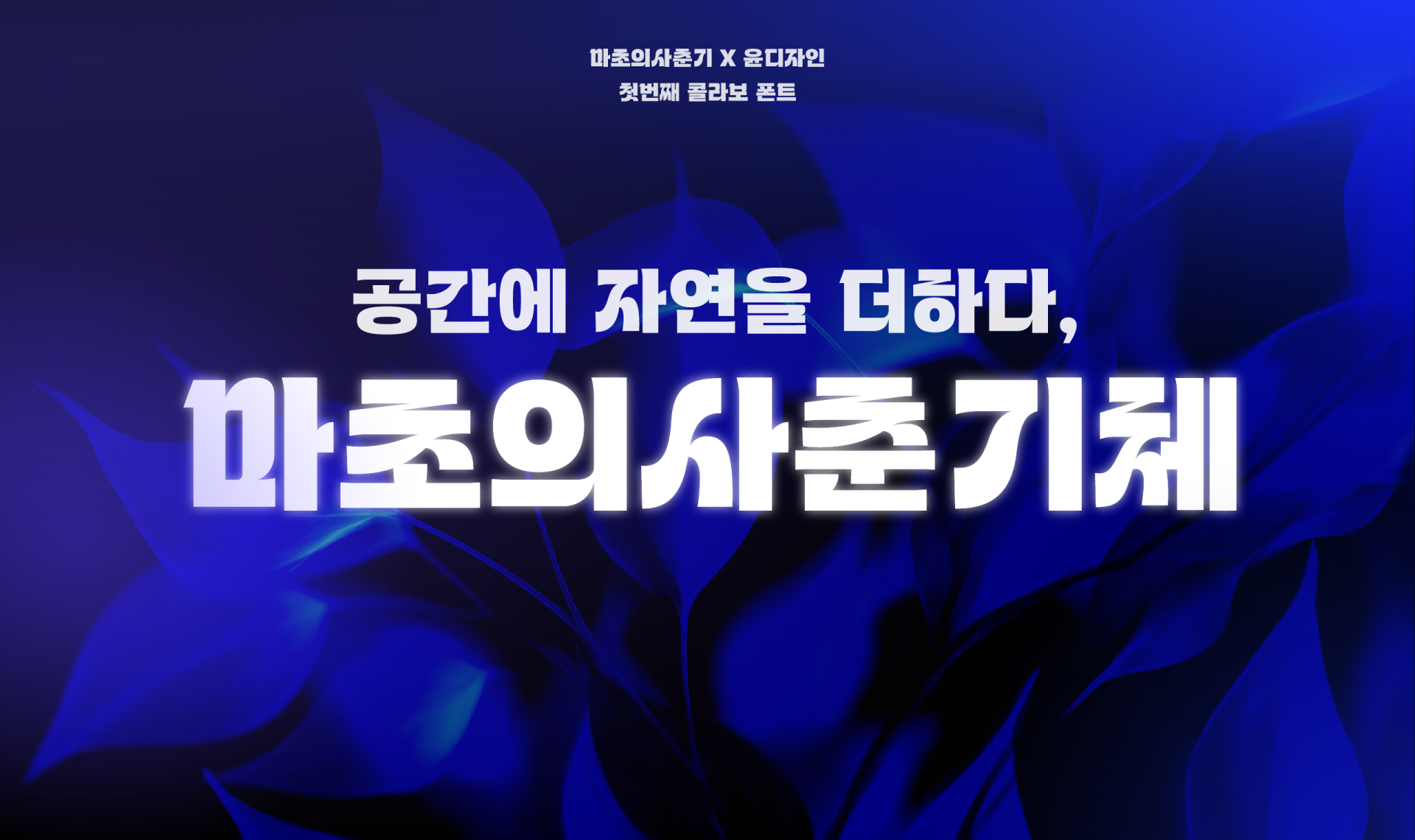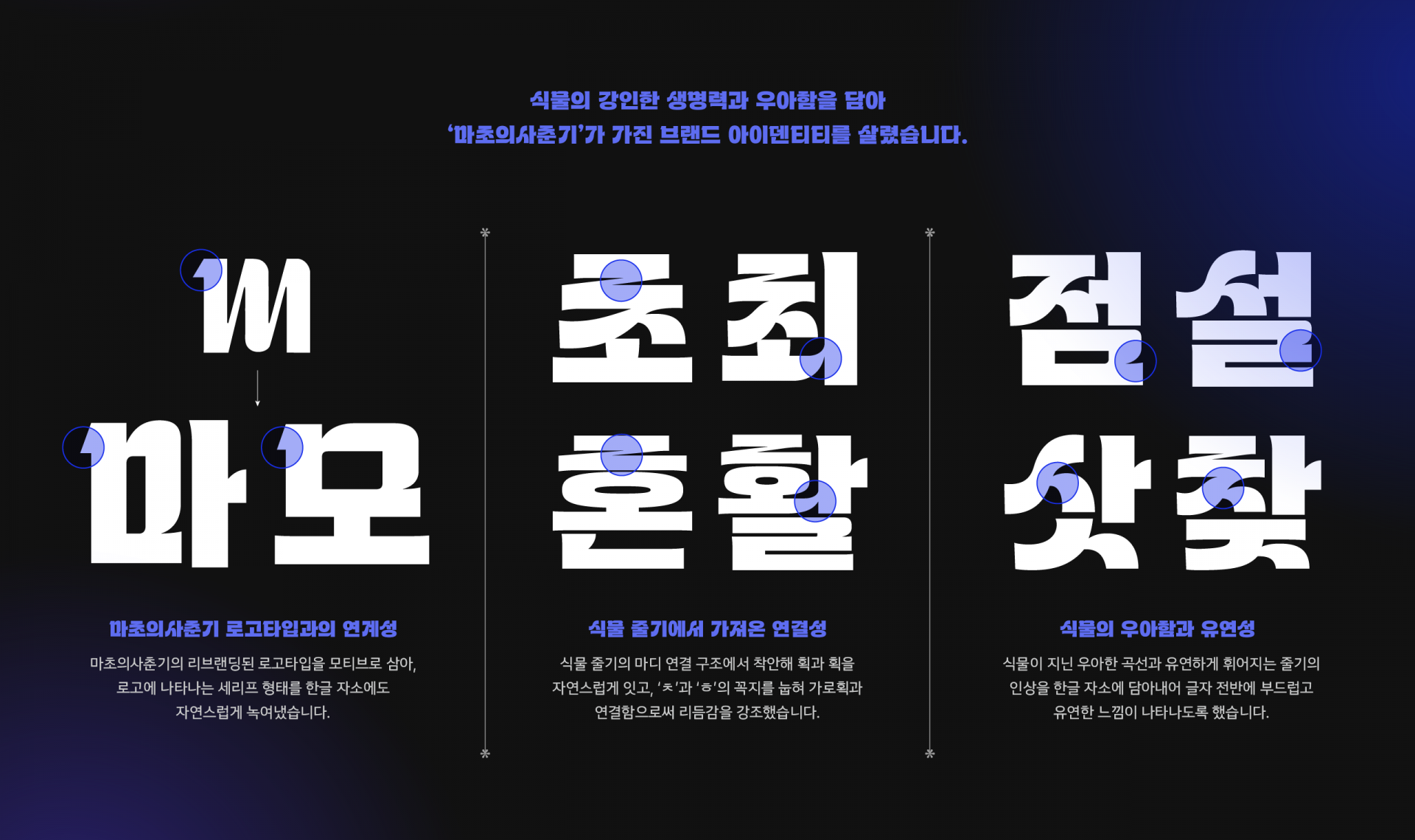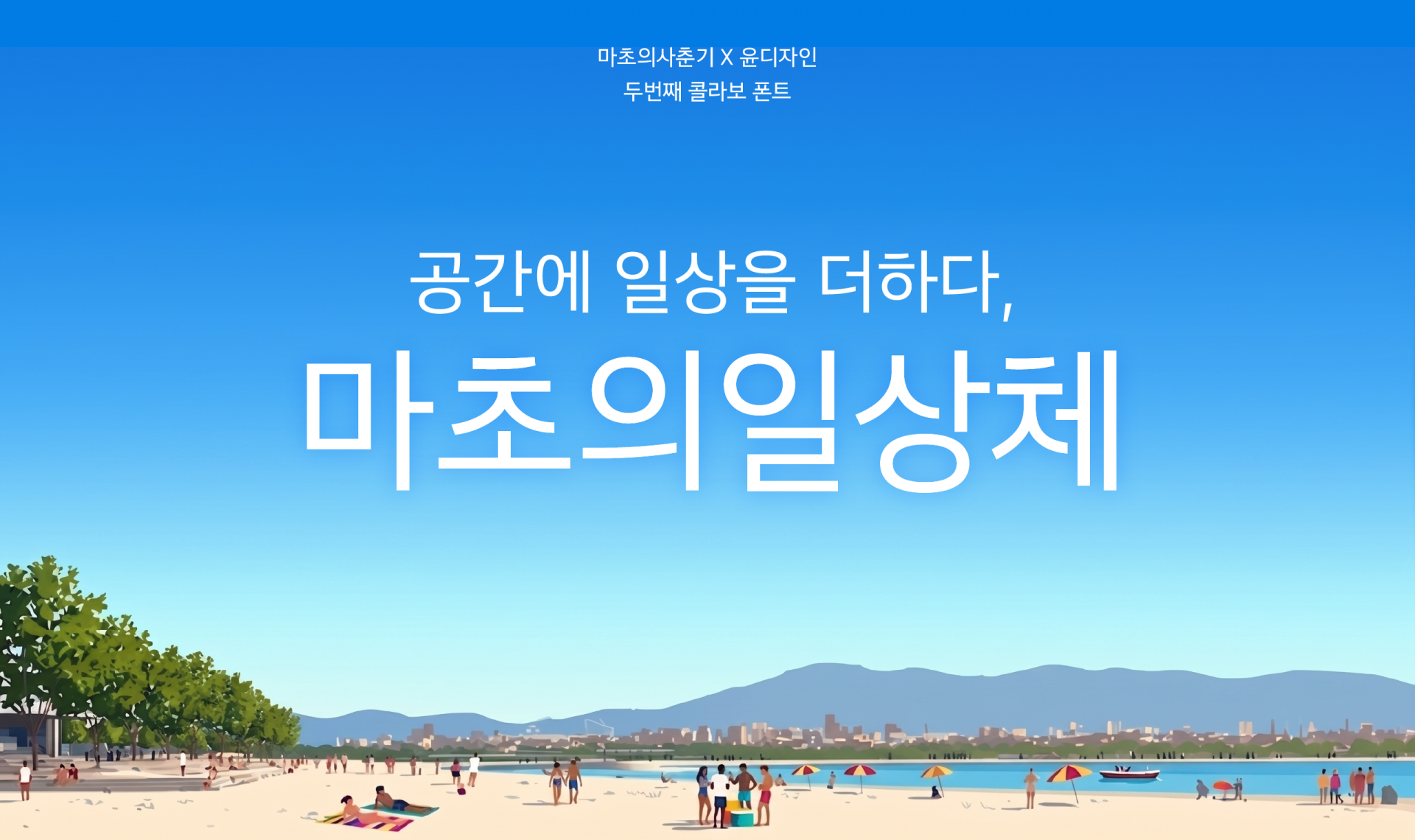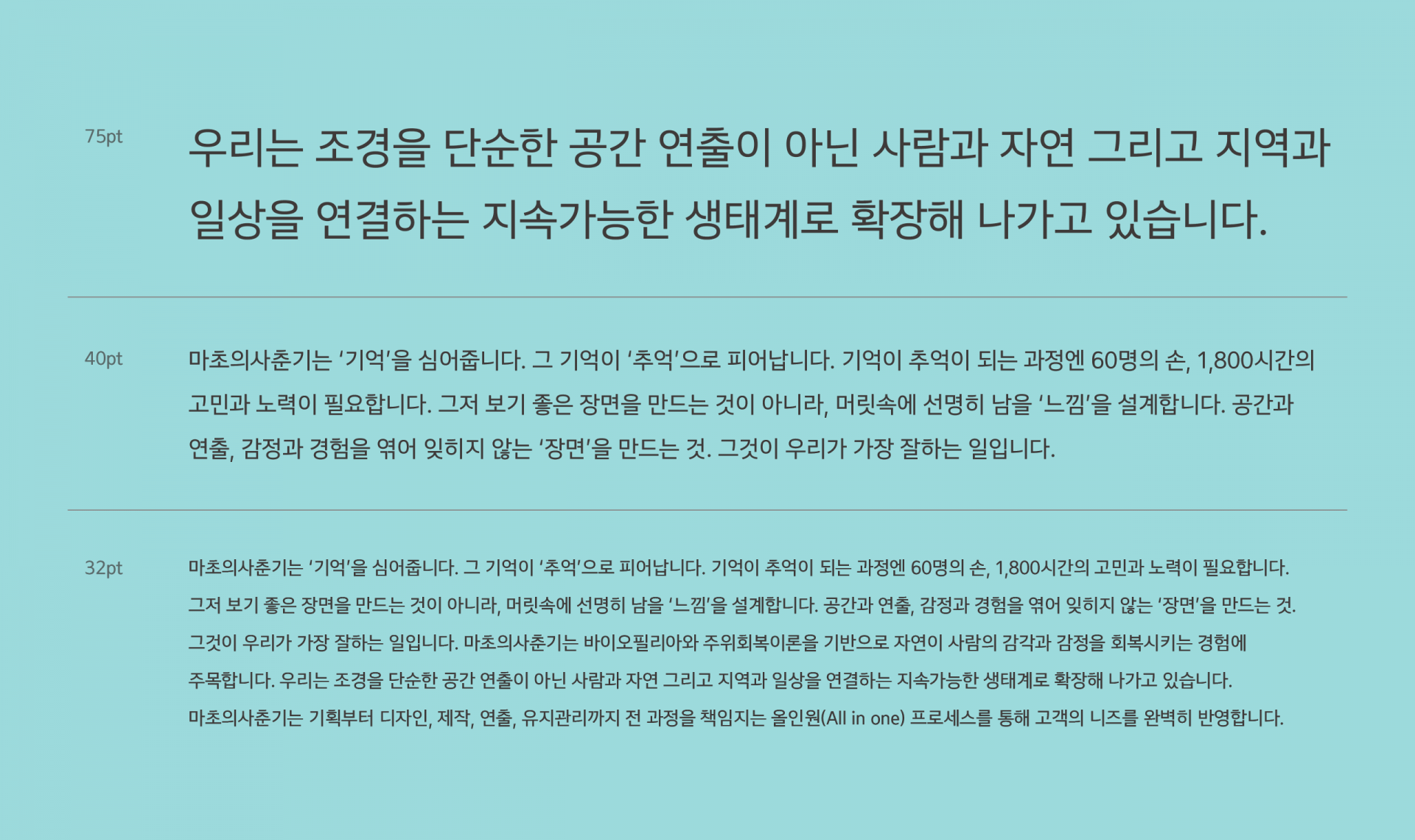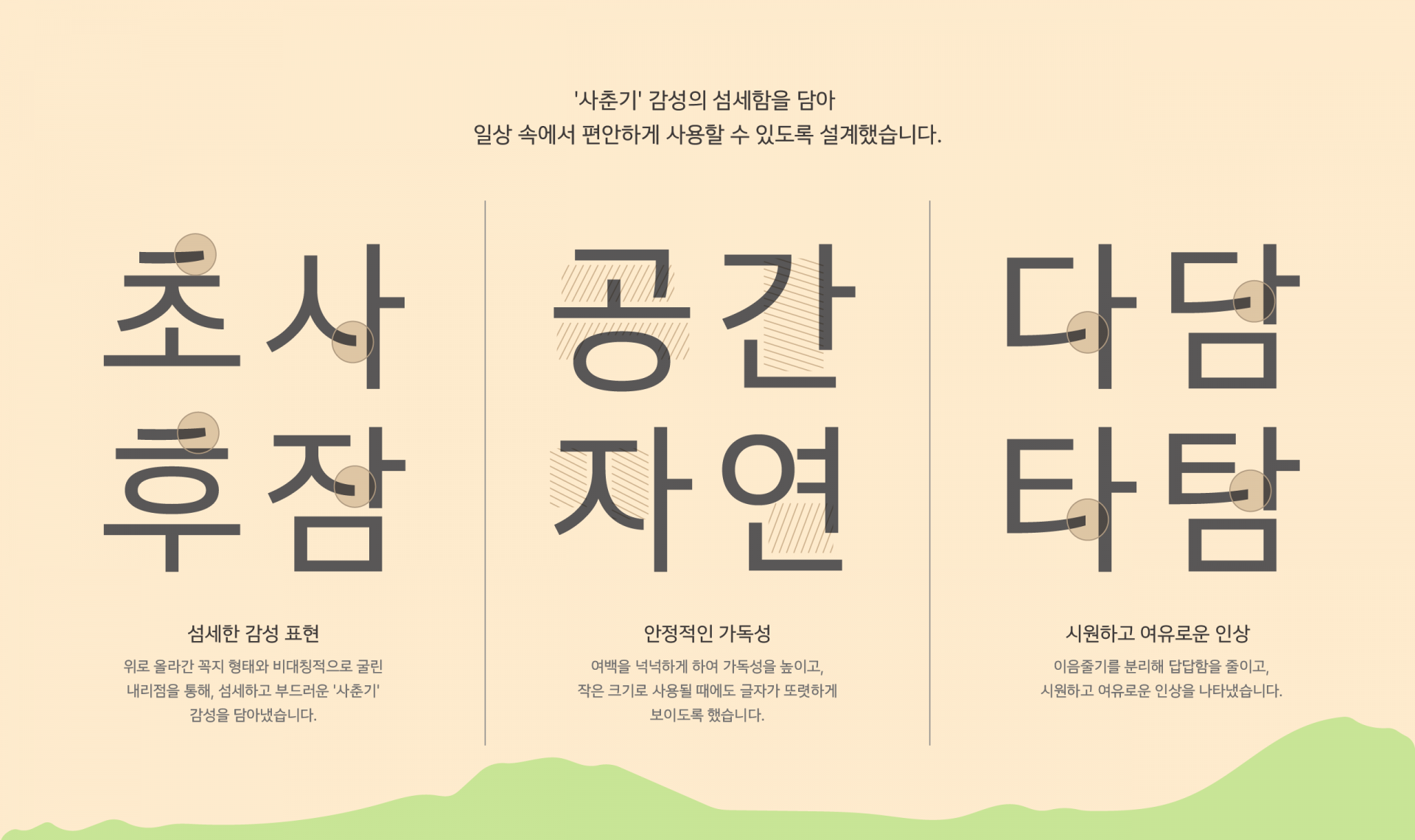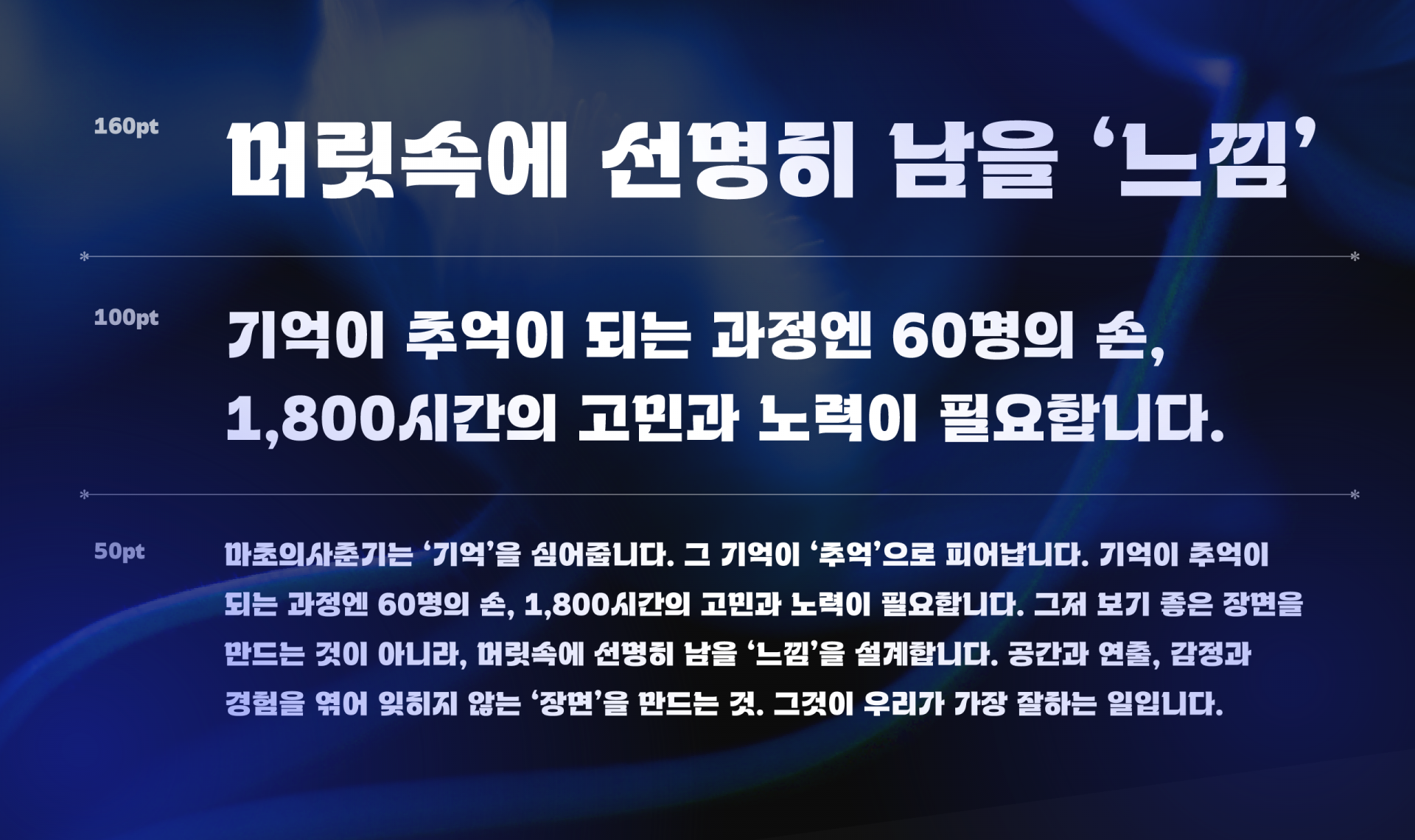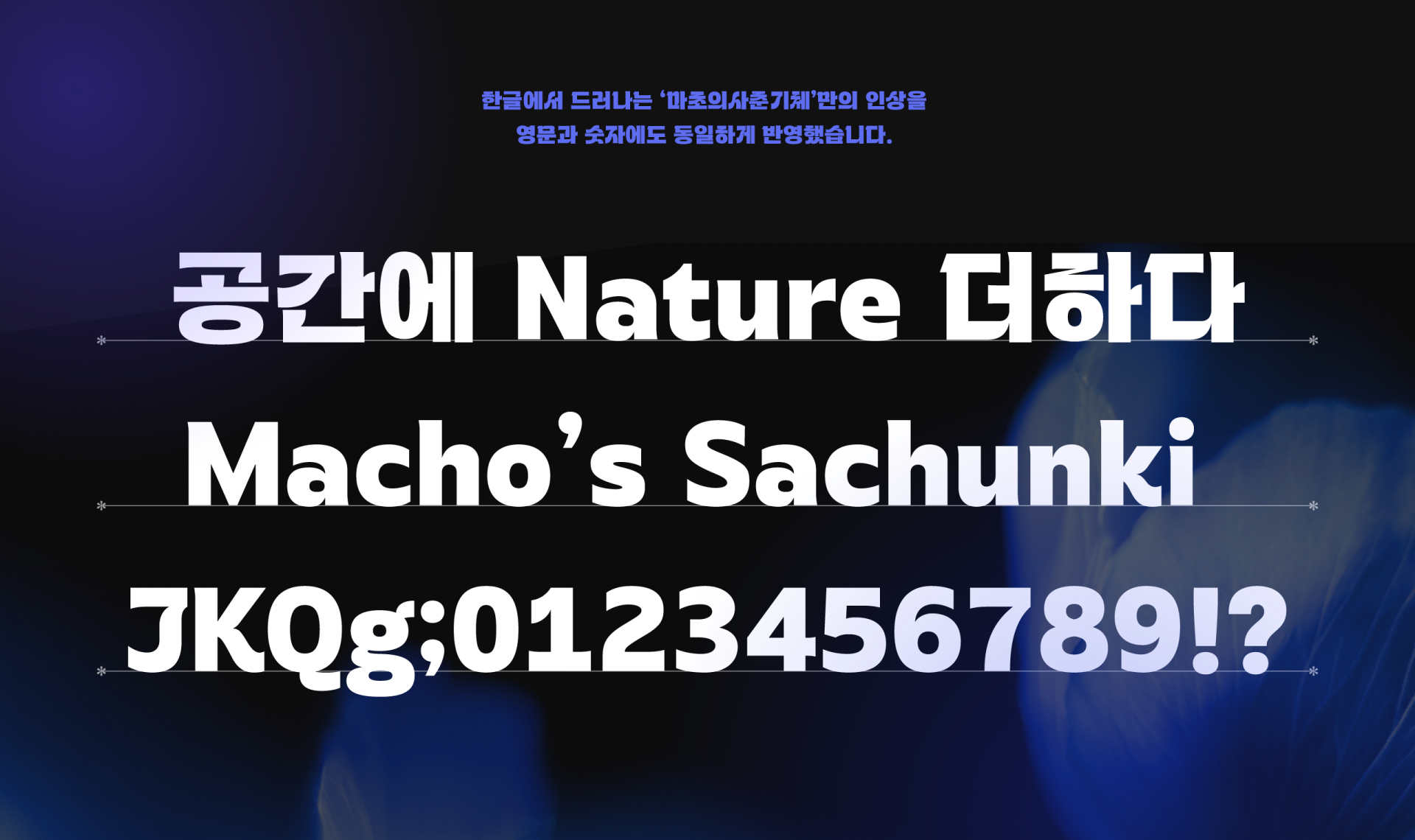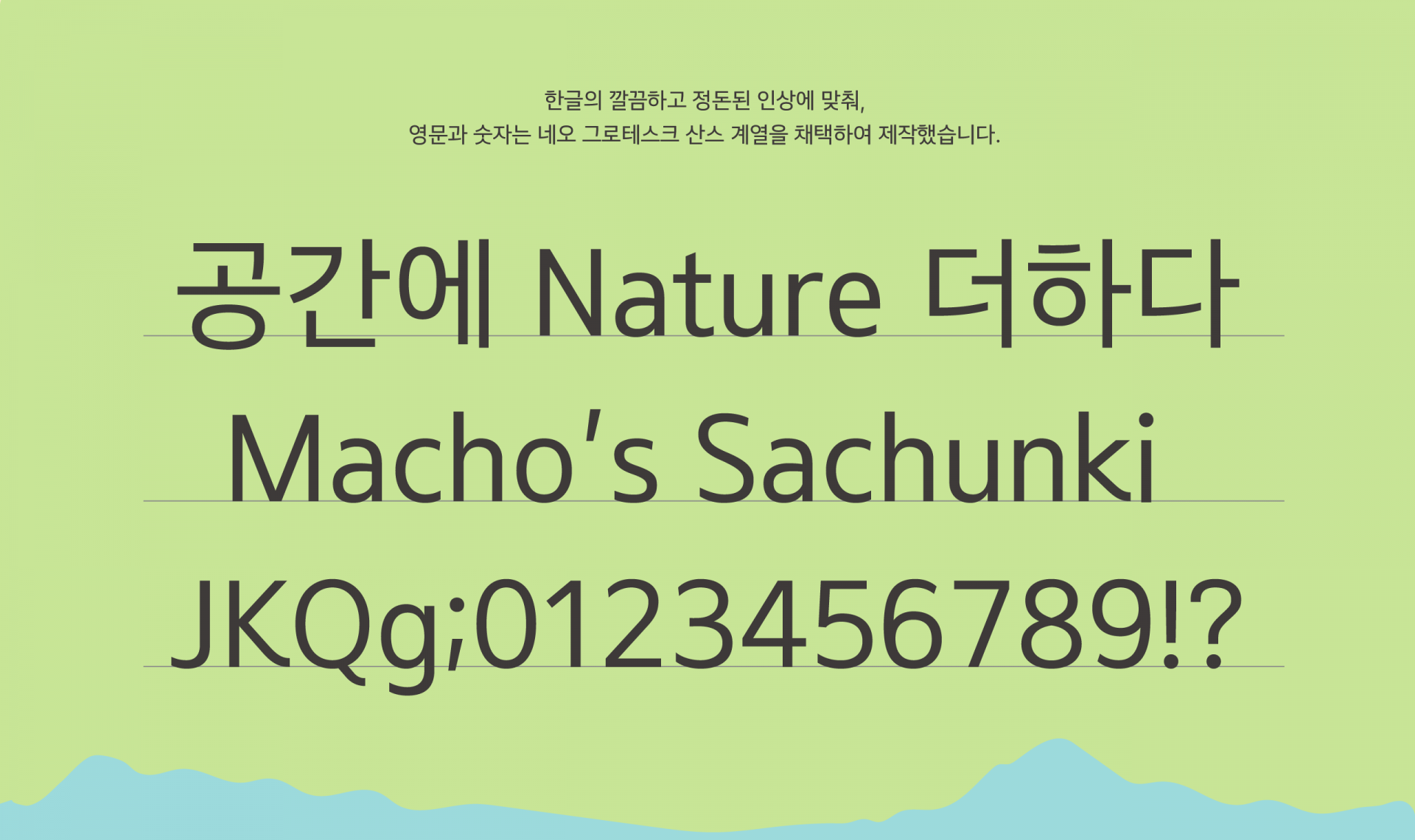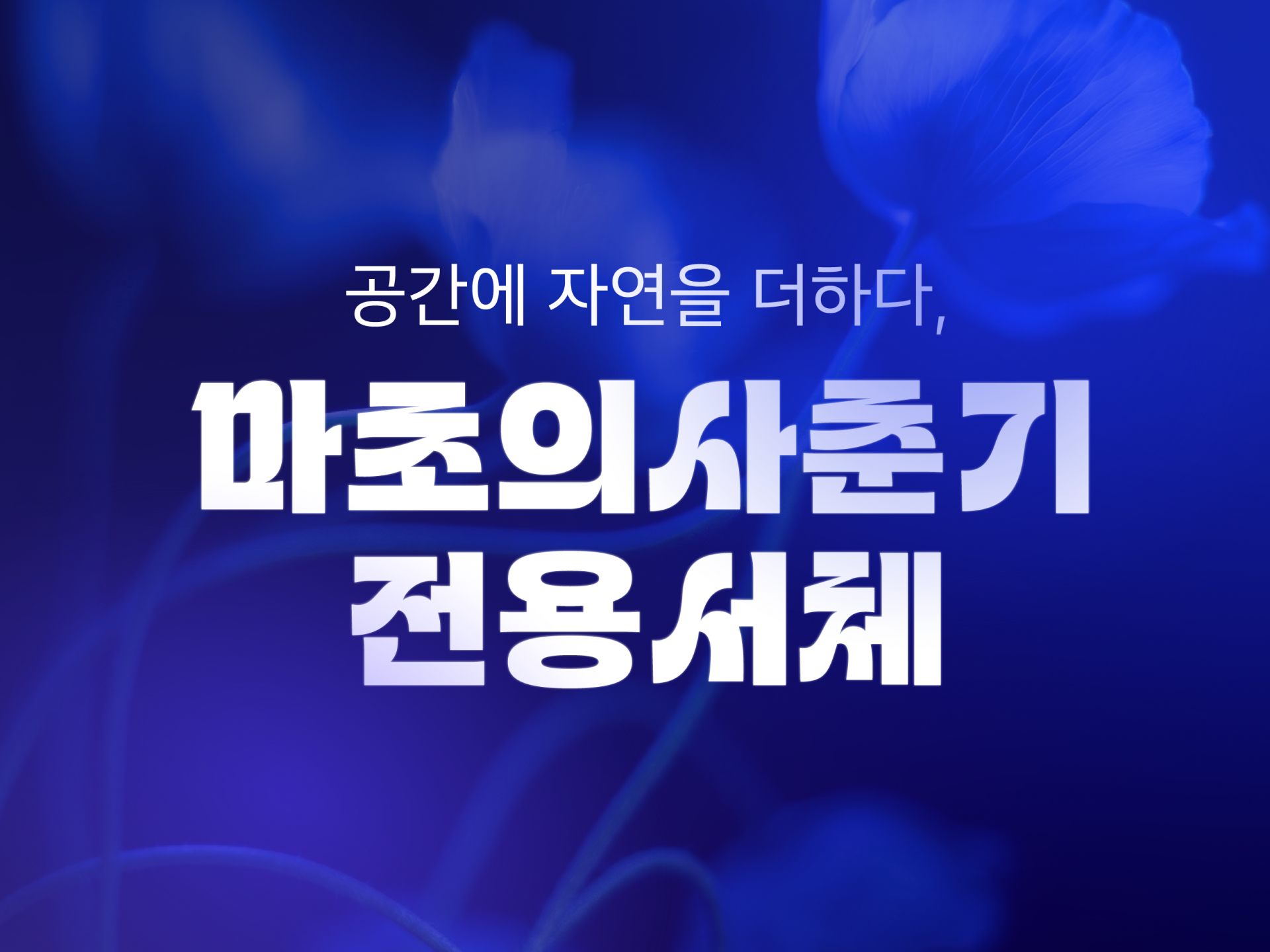
마초의사춘기 [마초의사춘기체, 마초의일상체]
[마초의사춘기체]는 리브랜딩된 마초의사춘기 로고타입의 조형적 특징과 식물로 공간에 새로운 가치를 더하는 '바이오필리아 디자인 그룹'이라는 정체성을 반영하여 브랜드만의 개성을 담았습니다. 식물이 가진 강인함과 우아함을 서체에 녹여내어, 유연한 곡선과 비정형적 형태로 생동감 있는 디자인을 완성했습니다.
[마초의일상체]는 속공간과 여백을 넉넉하게 두어 여유롭고 시원한 인상을 자아냅니다. 이음줄기를 분리해 글줄에 호흡을 만들고, 제목용에서 보이던 곡선적인 결을 본문용에서도 부드럽게 이어갑니다. 내림획에서 드러나는 비대칭적인 형태에 섬세하고도 예민한 사춘기의 감성을 담았습니다.